みなさんはこれまでに自分の名前を何回書いていますか。
数限りなく書いているので回数なんて分からない、という人がほとんどでしょう。
もちろん私も同じです。
みんなが数限りなく書いているはずの「名前の文字」。
この「名前の文字」についてびっくりしたことを今日はお話ししたいと思います。
ご本人の名誉のために、全ての登場人物を匿名にしておきましょう。
1 自分の名前の字
あるお父さんがいました。あるお母さんがいました。
その間に小学生の子どもがいました。
ある日、子どもが宿題で書いた文字があまりにきたなかったので
お父さんは言いました。
「字が汚すぎる。きれいに書かなくてもよいから、丁寧に書いてほしい。」
「お父さんは、お父さんのお母さんから
『文字のたてよこの線は最後までしっかり書きなさい。』
『いくつかの平行な線があるなら、その線の間は等間隔にしなさい。』
と教わったよ。」
「だから臨機応変にくずして書くのもいいけど、まずは基本として
等間隔で線を書きなさい。」
「たとえば、織田信長の『信』の文字。
『信』の『言』のよこ線は等間隔に書きなさい。」
子ども
「なるほど。言いたいことは分かった。」
お父さん
「分かればよろしい。」
「たとえば、あなたの名前の文字の『倫』だってそうだよ。
『倫』の『冊』みたいな部分の4つのたて線は等間隔にすべきである。」
子ども
「え?4つのたて線?」
お父さん
「え?何が『え?』なん?4つのたて線の話ですけど。」
子ども
「『冊』の部分って、中はカタカナの『サ』じゃないの?」
お父さん
「え?何の話?『冊』の中は、カタカナの『サ』だと思ってたの?」
子ども
「え?違うの?」
お父さん
「マジか。自分の名前の字だぞ?」
子ども
「だって幼稚園の年長のときにお母さんが
『そこはカタカナのサみたいなものよ』
と言ってたから・・・。」
(ごそごそと電子辞書を取り出し「倫」を調べ始めて)
子ども
「・・・マジか・・・。」
お父さん
「今までずっと書いてきたのか。そうだ!リビングに習字が
飾ってあったぞ。筆ならちゃんと書いたのでは?」
お父さんと子どもはリビングの習字を見つめました。
それでは読者のみなさんもごらんください。
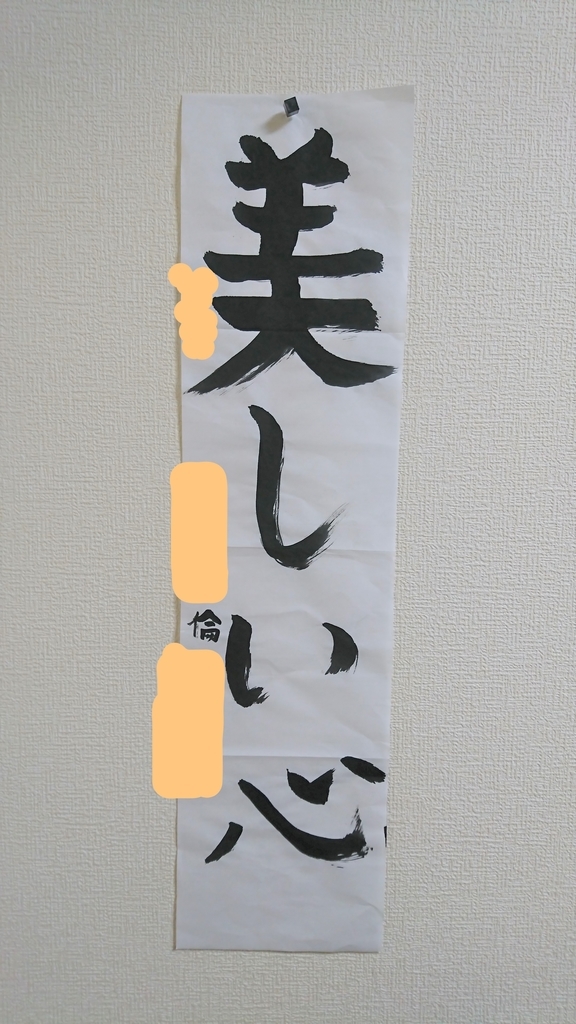
拡大して見てみましょう。
さらに拡大!
お父さんと子ども
「ああ~っ。」
お父さん
「たしかに『サ』・・・。」
もう『サ』しか目に入らない(笑)
「美しい心」なんてどうでもいい(笑)
お父さん
「今まで何回書いたんだよ。」
「こうなる前に誰か言ってあげてよ。」
「でも・・・気づかないかも(笑)。」
「世間と本人のギャップ、なんか笑えるw」
読者のみなさん、どうですか?気づきますか?
『サ』という意識で見れば明らかに『サ』と気づきます。
ですが、ふつうは気づかないでしょう。
2 誤字とは何か
倫理の「倫」の字の「冊」のような部分。
その中身がカタカナの『サ』だと思って、実際に『サ』と書いている。
これは厳密に見れば、「倫」ではないので
「倫」の誤字
といえるでしょう。
でも、見て下さい。
何の先入観も持たない人がこの文字を見れば
100人中100人が「倫」と読むのではないでしょうか。
そうするとこの文字は「倫」と読めるので
誤字ではない
とも言えます。
どこまでが誤字で、どこまでが誤字ではないのか
お母さんは
「力を入れ過ぎずに文字を書いてもらうために
『サみたいなもの』と確かに言いました。」
「私はそう書いています。」
と言っていました。
つまり、お母さんは確信犯なのです。
笑っているそこのあなた!
あなたの名前の文字は大丈夫ですか?
他にも、2つの異なる文字なのにくずして書くと
似てきてしまうことがあります。
たとえばこんな話があります。
上杉家関係の古文書を解読されている
la_cometa_rossaさんのツイッター
書く方の意識した文字と
読む方の意識した文字が違うとき。
その線の集まりは、誤字なのでしょうか。
どこまでが誤字ではないのか。
誤字の「誤」はどんな場合を表すのか。
直感的にはかなり深い問題のように感じています。
画像認識、文字認識(OCR)として機械的に分析すべき話かもしれません。
機会を改めてもう少し深めて考えてみたいと思います。
それにしても、思い込みってこわいですね。
子どもにとっては(早くもないですが)気づいてよかったと思われます。
お父さんはこの時以来リビングの習字の文字を見るたびに
ニヤニヤしてしまうらしいです。